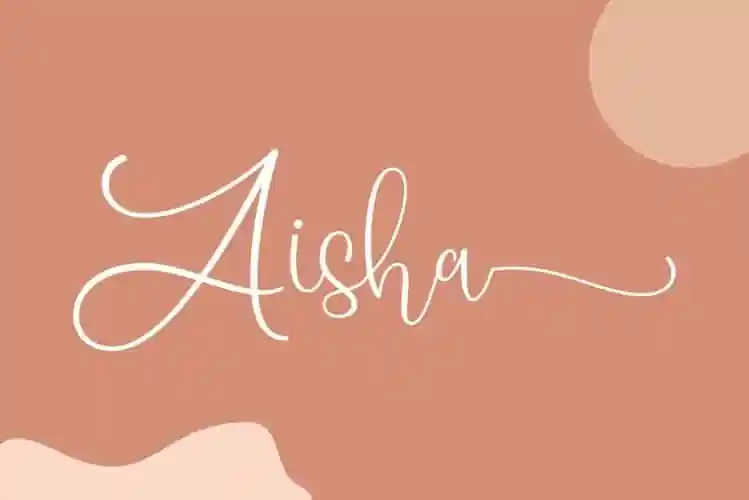
Aisha Calligraphy Font é uma fonte script única que mistura elementos clássicos com modernidade criados pelo designer dickykribo. Suas letras têm um toque imperfeito, representando os movimentos fluidos e deslizantes de um belo danço. As linhas são limpas, simples e elegantes, proporcionando uma sensação suave e natural. Este recurso é perfeito para aqueles que buscam uma fonte com personalidade e estilo único para projetos visuais interessantes. Aisha Calligraphy Font inclui vários alternativos para agradar todas as necessidades de design gráfico, tornando-a uma opção inovadora para o seu próximo projeto.